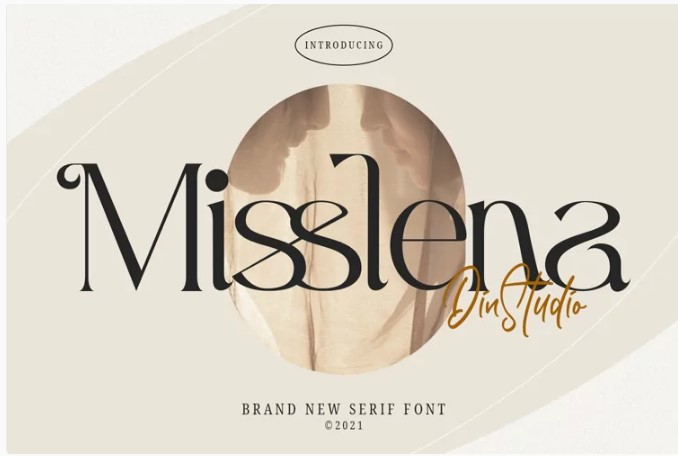
[Fontbundles] Misslena Font (2021)
Один из самых элегантных, изысканных и в то же время сильных шрифтов.
Misslena создан для того, чтобы придать современный и стильный вид тому, что вы создаете. Этот шрифт содержит символы верхнего и нижнего регистра, все знаки препинания и цифры. Также в шрифте есть лигатуры и чередующиеся символы, которые помогают тексту течь естественно и придают ему индивидуальность. Его легкий вес хорошо подходит для основного текста. Доступные стилистические альтернативы предлагают множество различных символов, которые придадут вашему логотипу или визитной карточке уникальный вид.
Misslena включает многоязыковую поддержку, чтобы ваш брендинг охватил глобальную аудиторию. Вдохновите свою аудиторию, клиентов или гостей с помощью этого красивого, выразительного шрифта.
Особенности:
Лигатуры
Альтернативы
Цифры и пунктуация